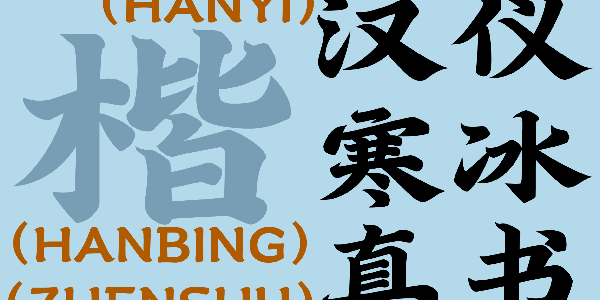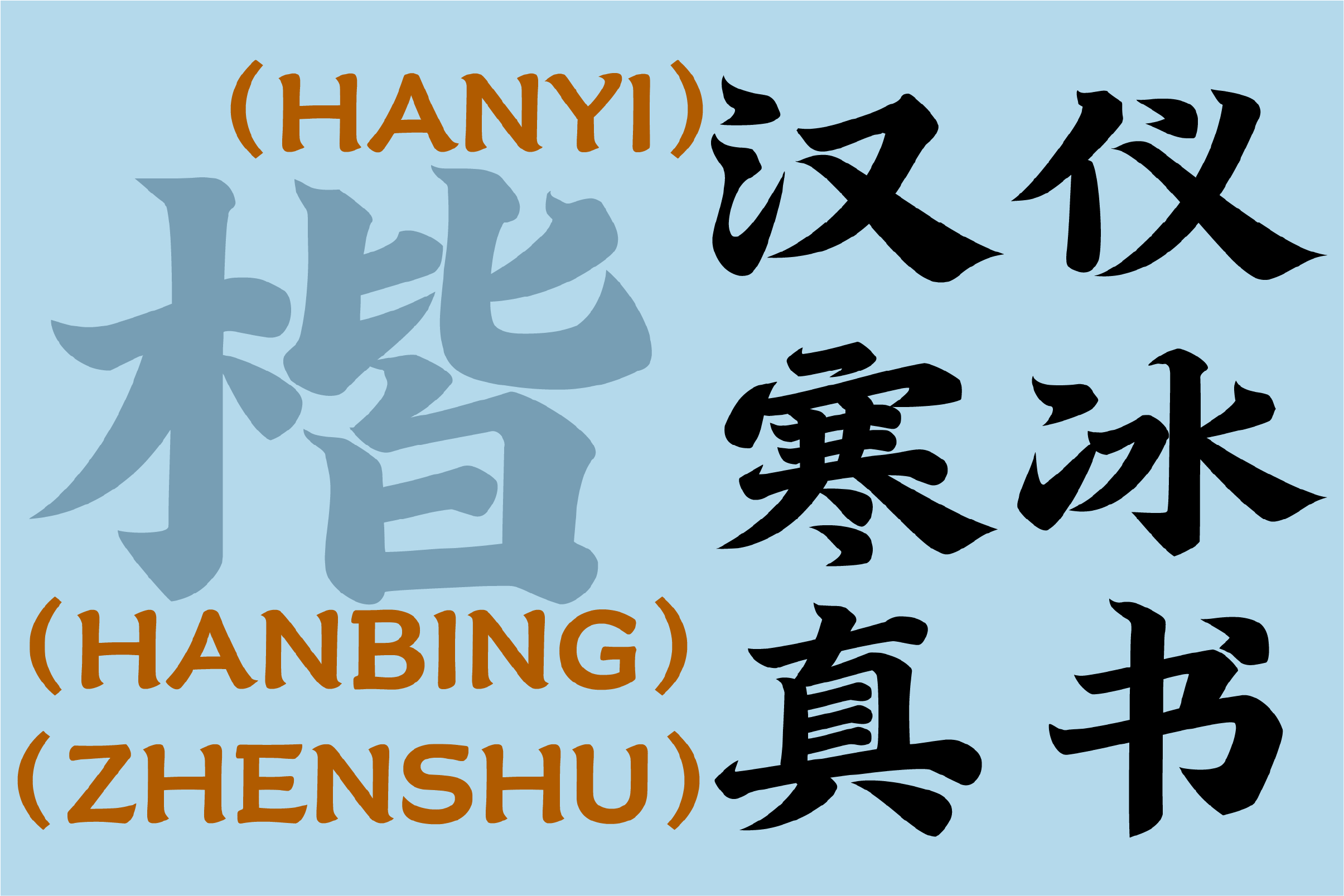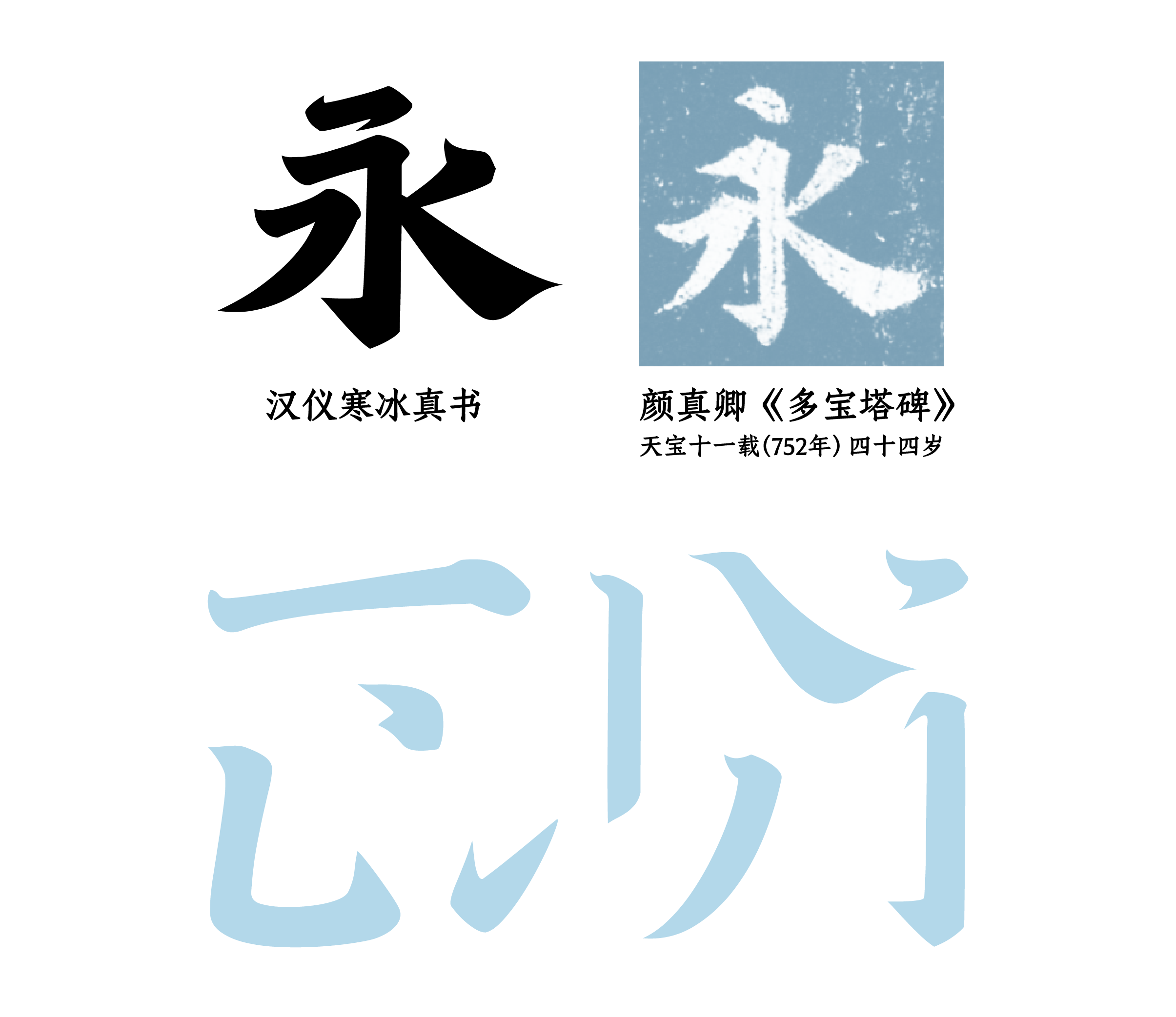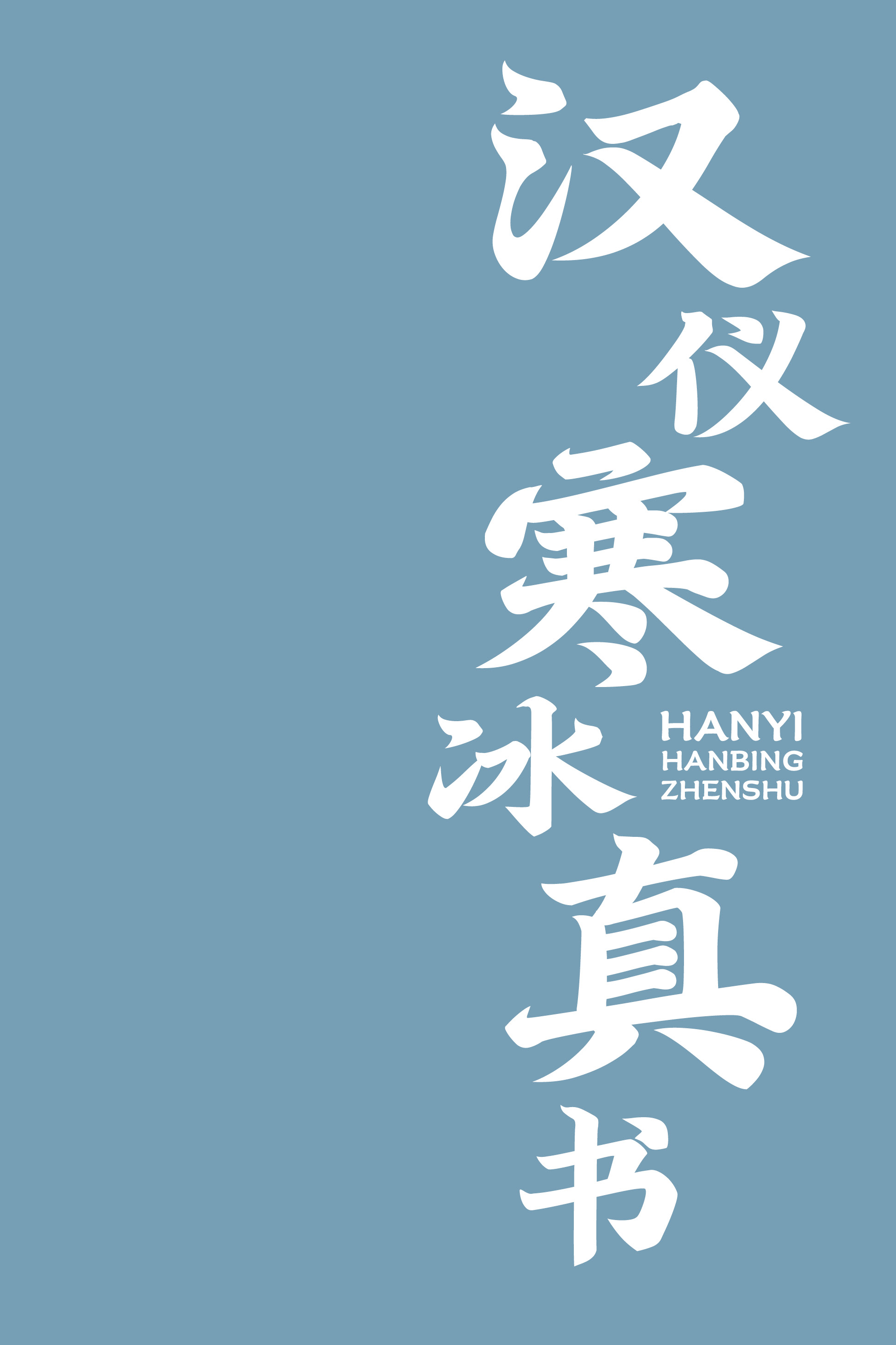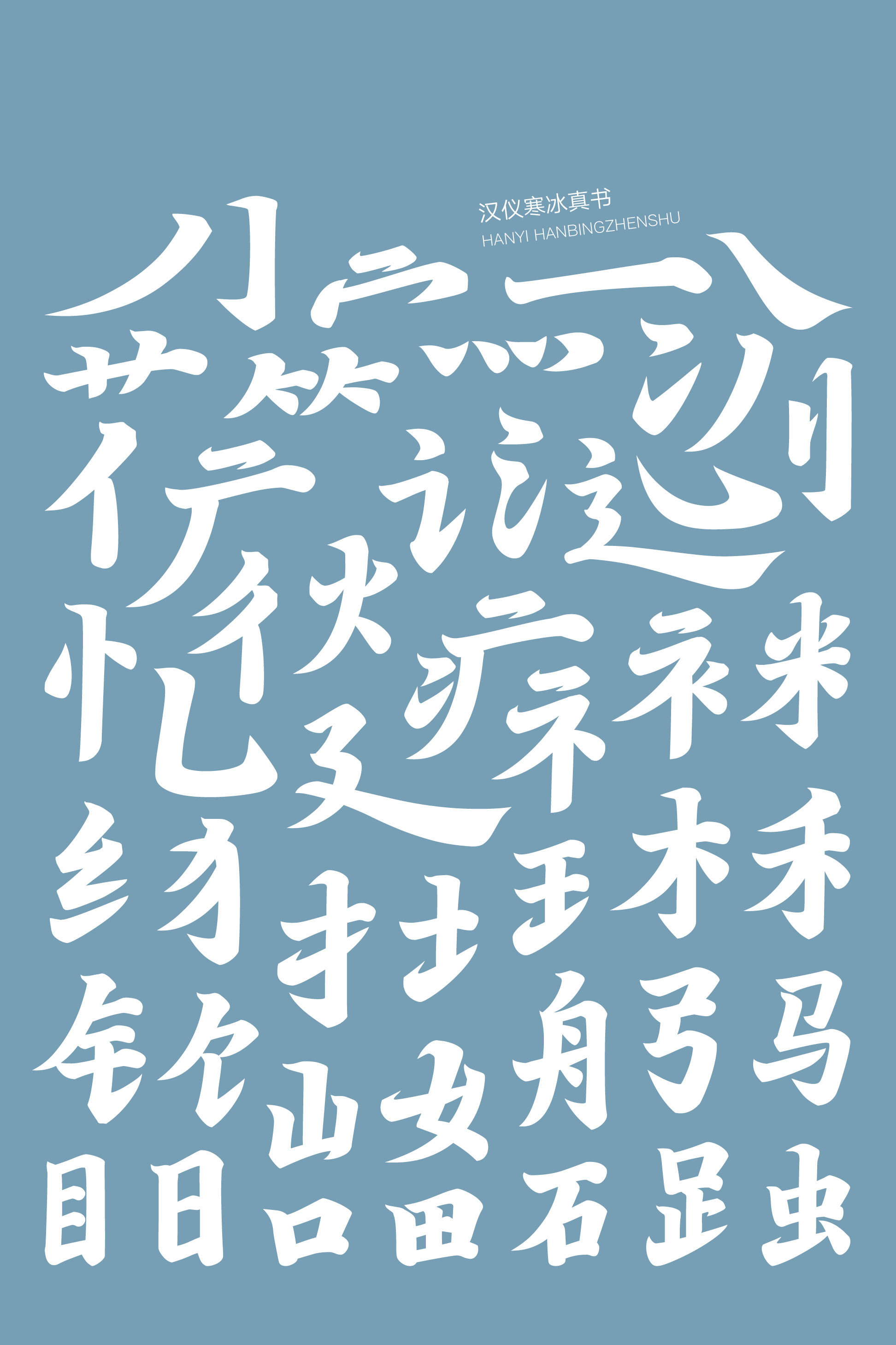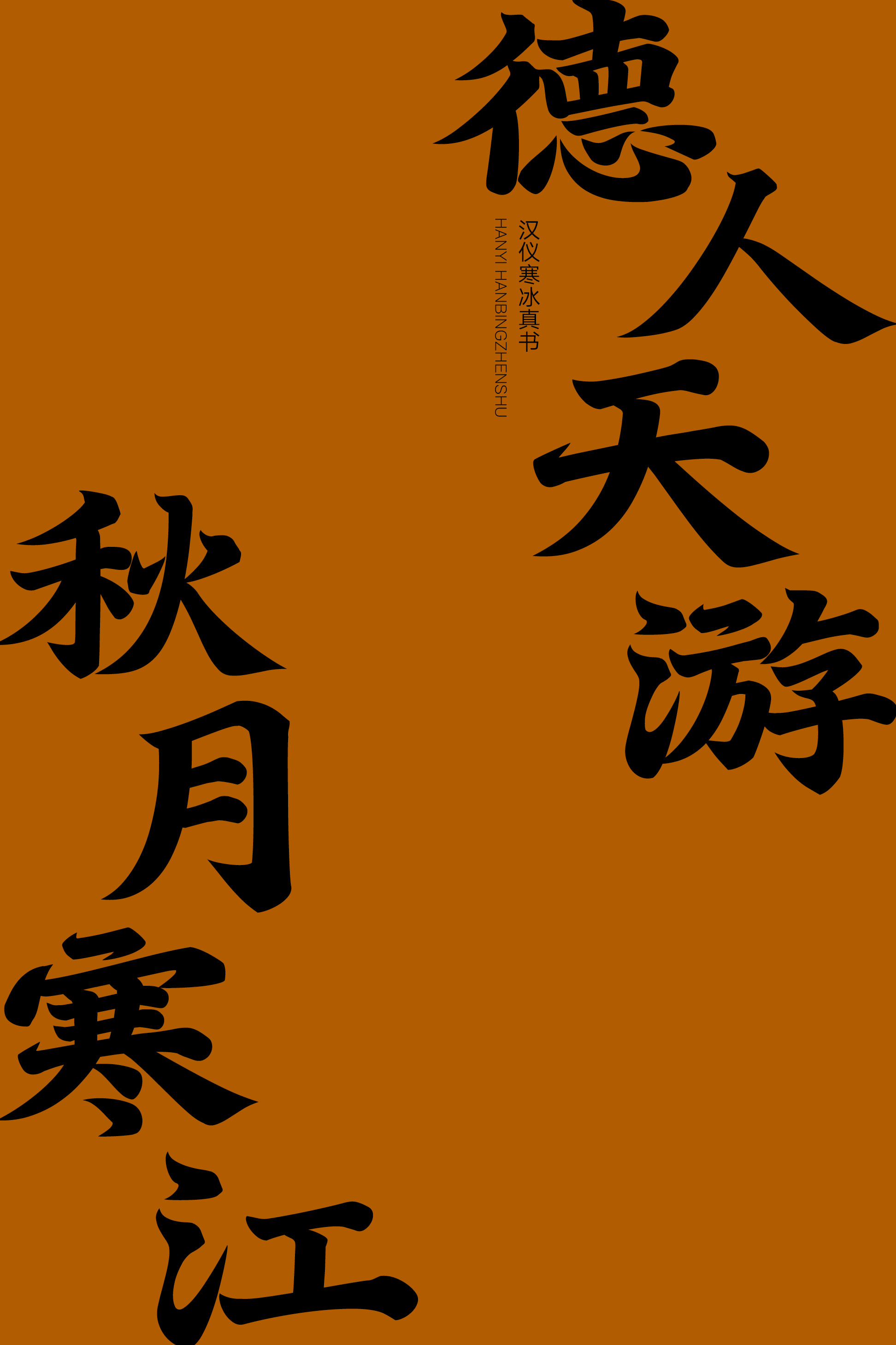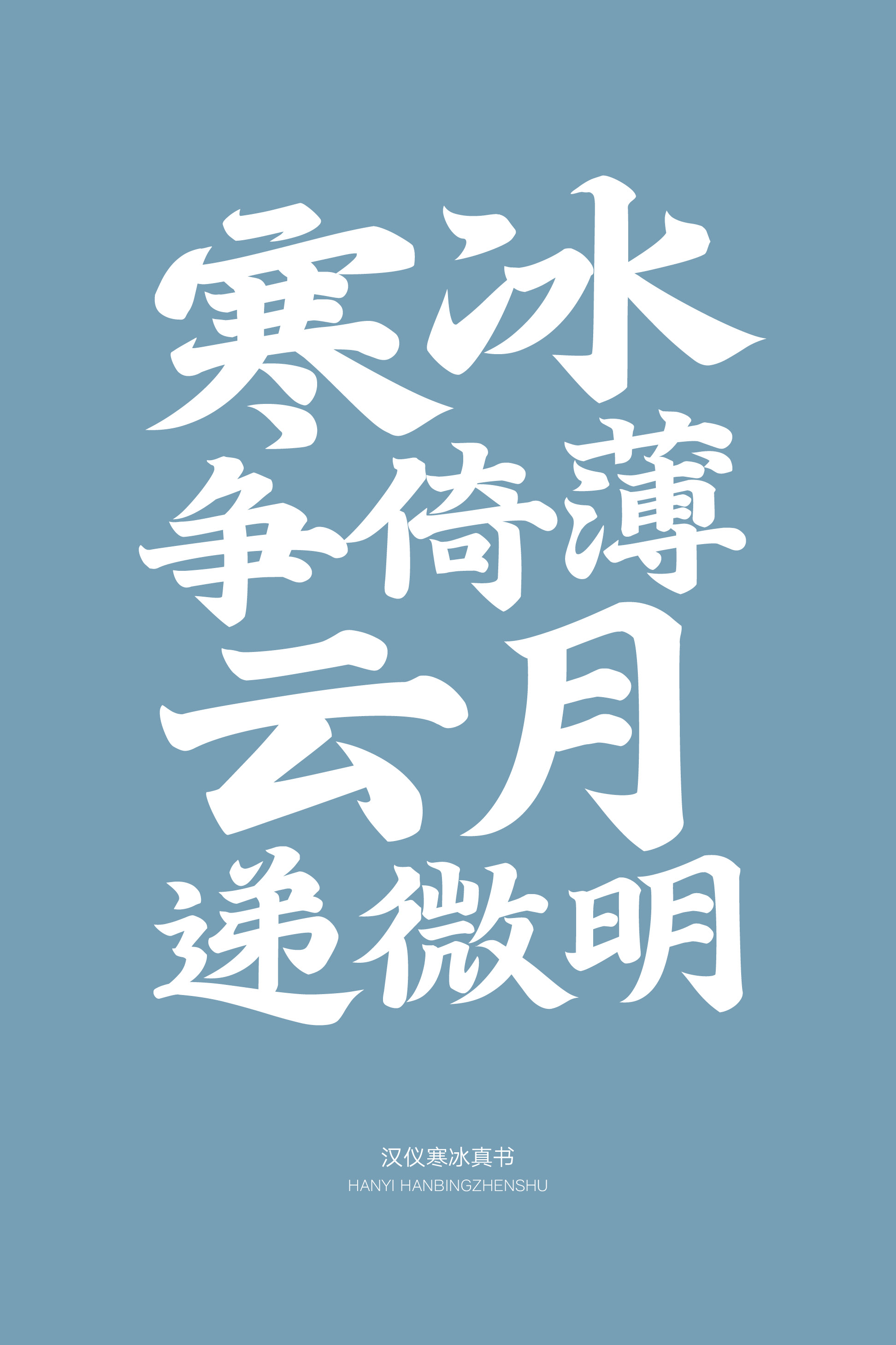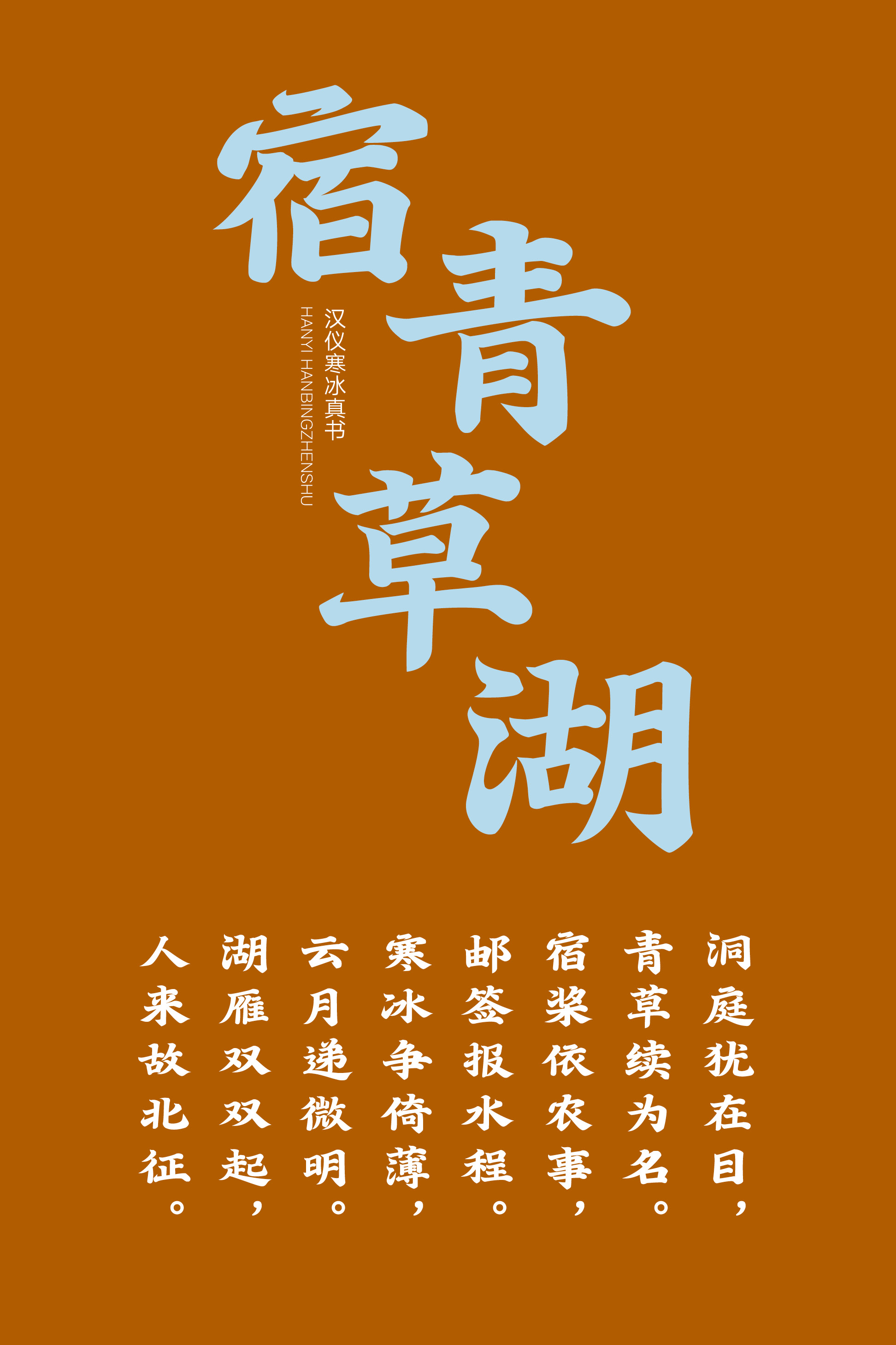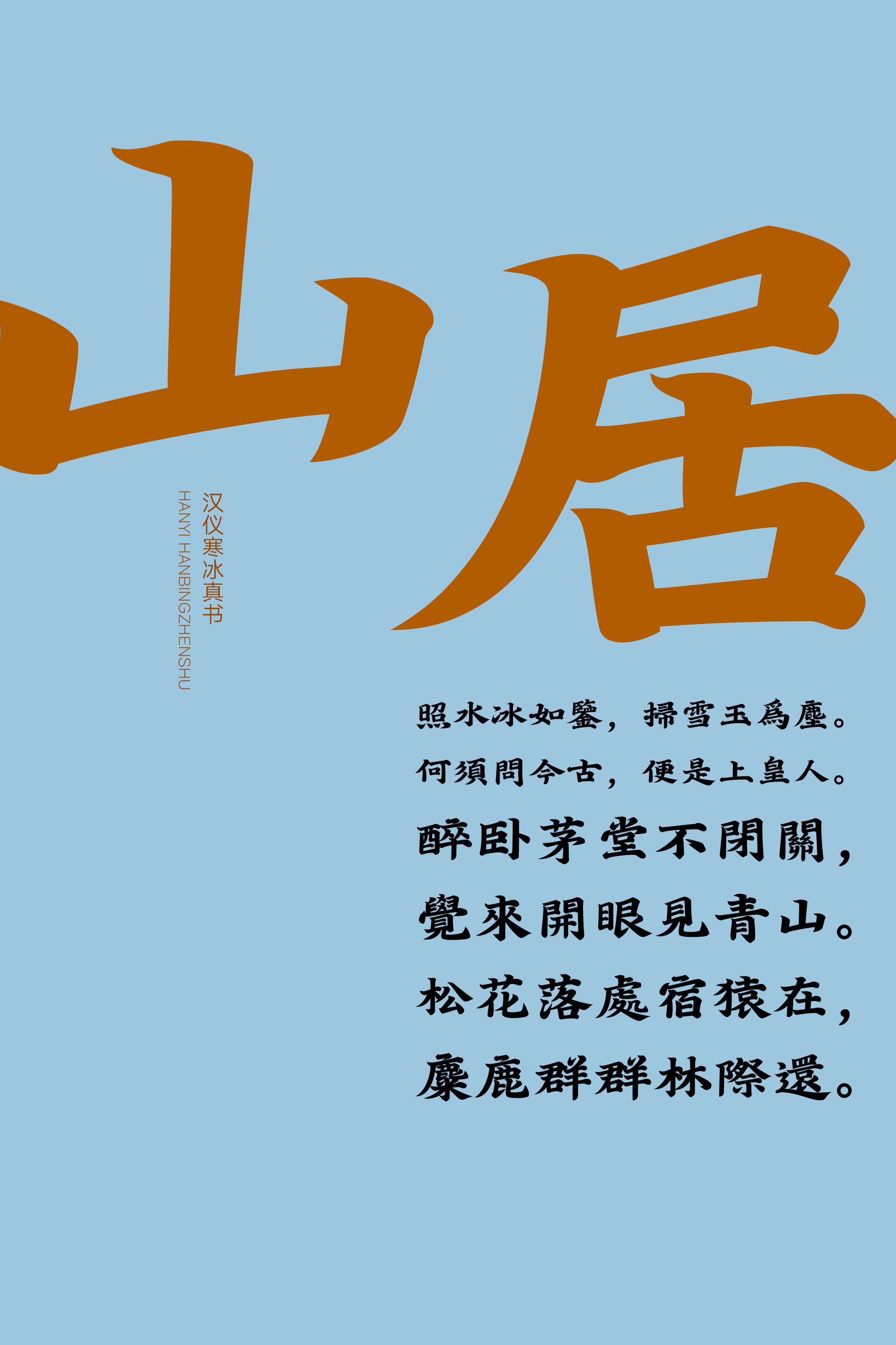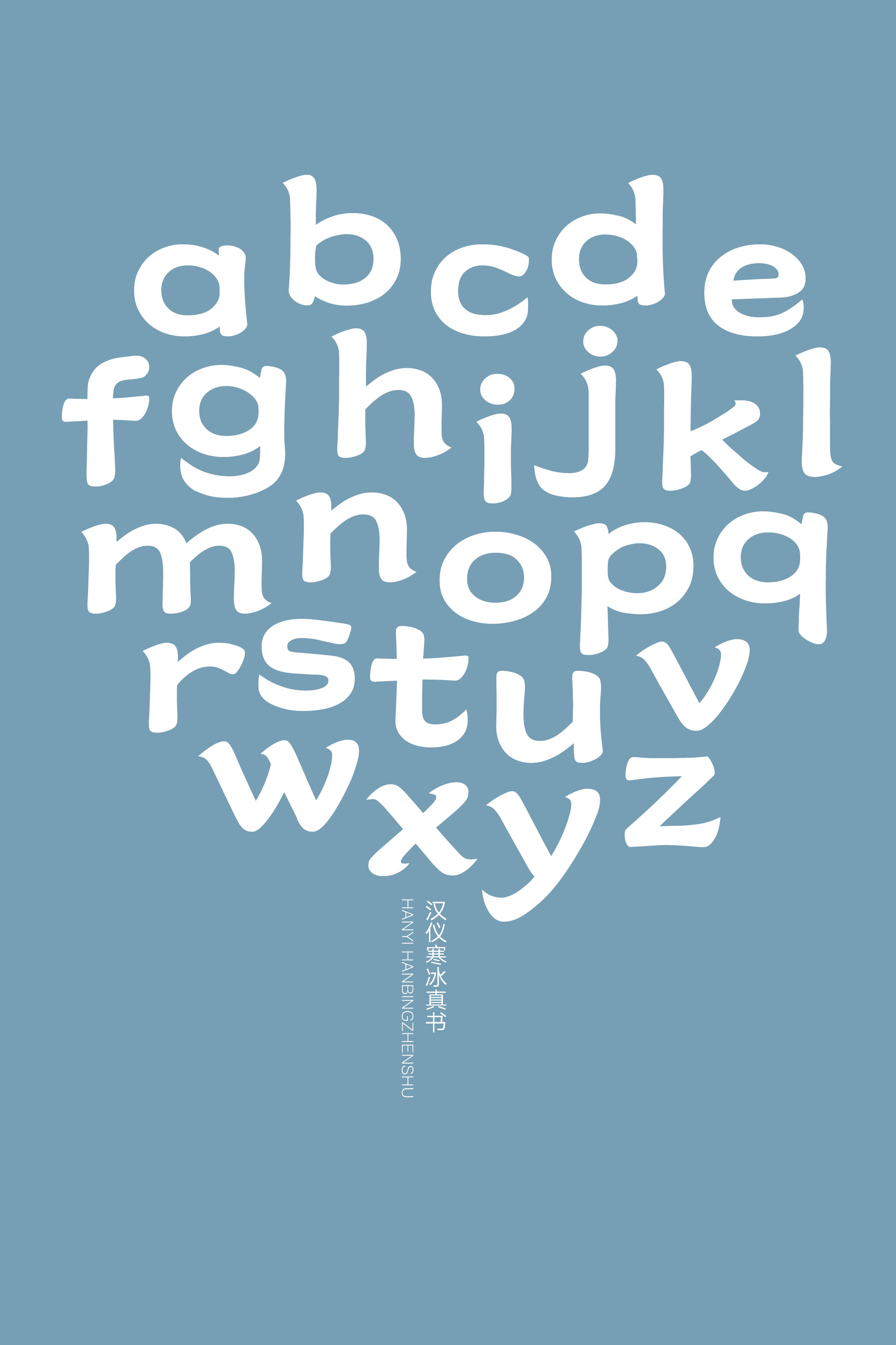
汉仪寒冰真书
汉仪寒冰真书,习颜楷之笔力弥满、气度森严,字形宽博,重心微沉。在设计中融入刻本字体对于笔画的处理方式,力道强劲,整体古典气息浓重。这款书写风格标题字体气象恢宏,蕴含中式古典韵味,适合用于招牌广告、标识包装等使用场景。
字形取扁势,重心略向下沉,稳重端庄。
左收右放,略向右上扬起。
习颜真卿中年时期粗而强劲的骨骼,笔力弥满,恢弘有力。
收笔凝重,骨外有肉。
汉仪寒冰真书的西文匹配采用拟古的思路,以工整大方的字形和略带书写笔意的起收笔与中文对应,整体古韵盎然。